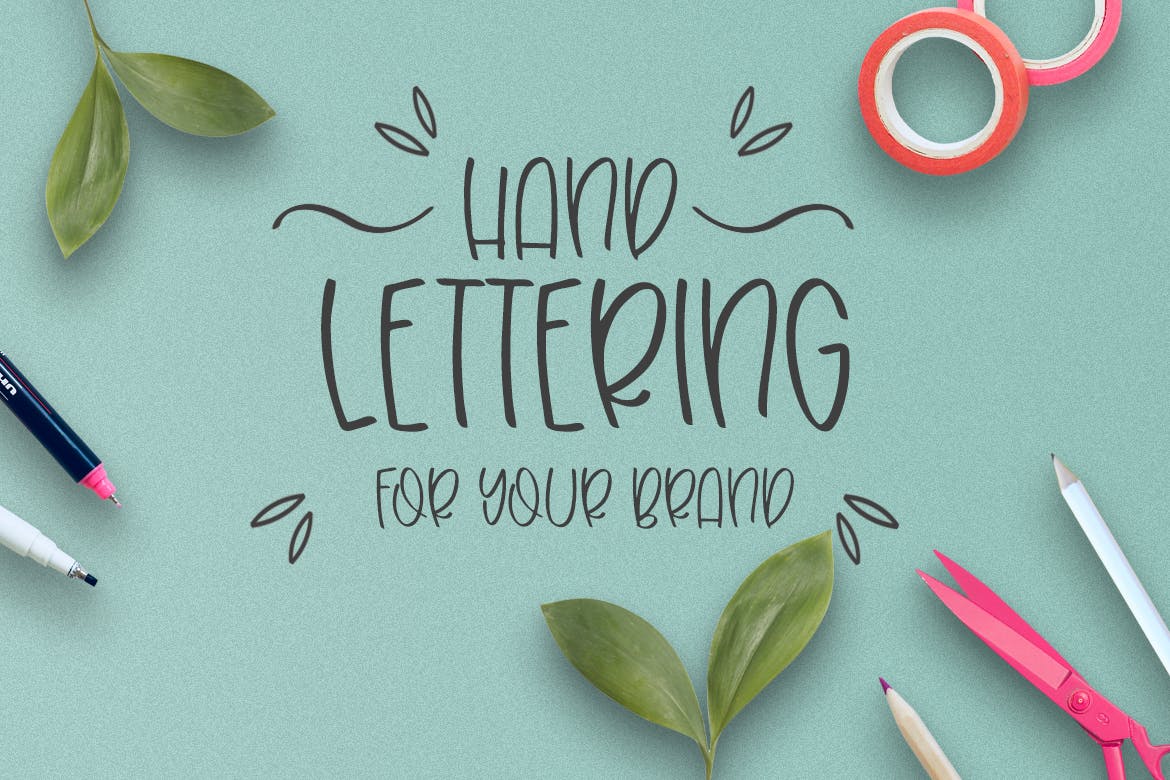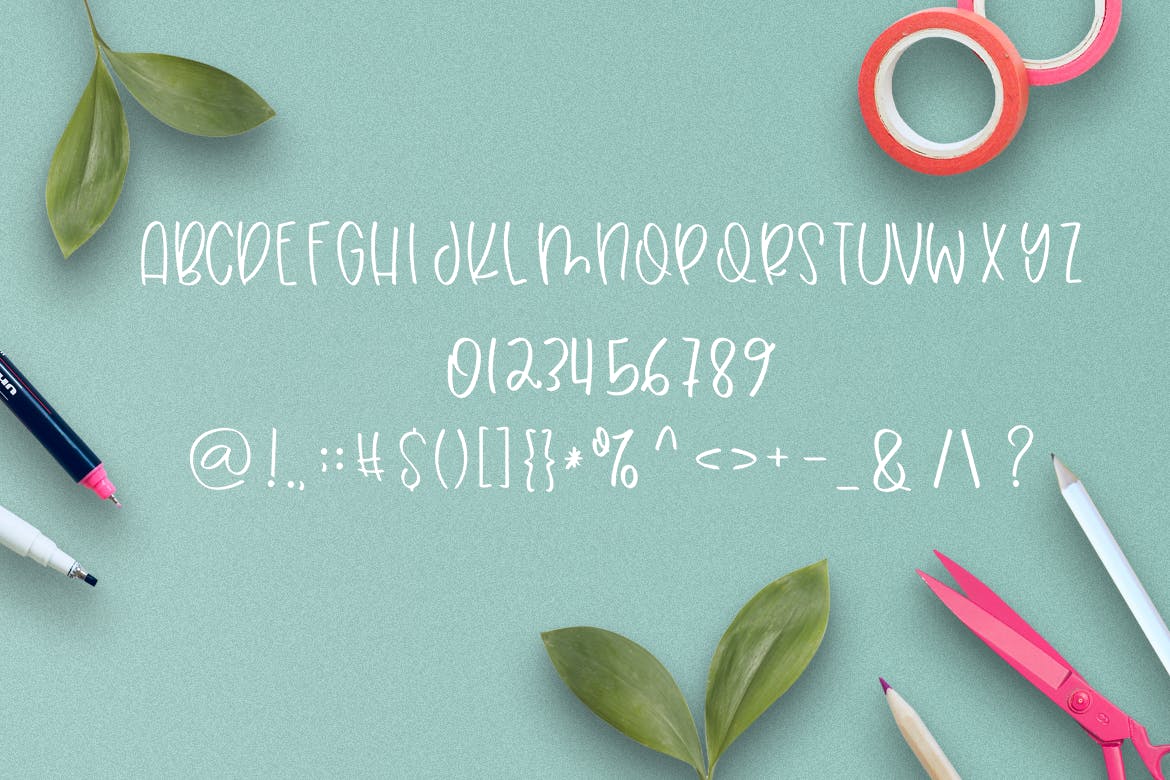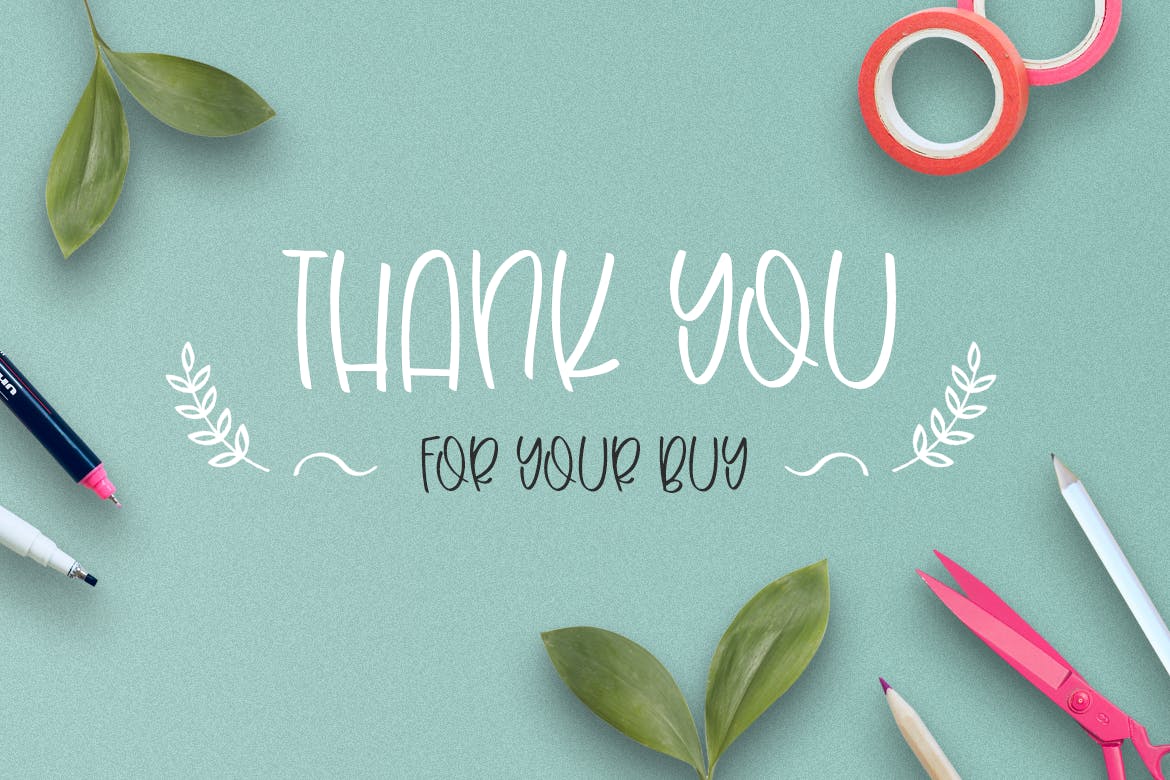
فونت جدید ما را معرفی میکنیم: Geovika Font - فونت مدرن
Geovika Font - فونت مدرن، یک فونت نمایش برجسته و اصیل است. این فونت برای هر پروژه برندینگ مانند لوگو، چاپ تیشرت، ورزشهای الکترونیکی و بسیاری دیگر مناسب است و در طیف وسیعی از زمینهها برجسته عمل میکند.
قابلیتهای این فونت شامل: